Titelvergabe Fonts Handbuch
Historisch gesehen war eine "Titelschrift Font" eine Font Metallschrift, die speziell für die Verwendung in großen Displays entwickelt wurde. Meistens handelte es sich um einfarbige Großbuchstaben, die zur Ergänzung von Textfamilien entwickelt wurden. Sie unterscheiden sich von ihren Text-Gegenstücken dadurch, dass sie speziell dafür entworfen wurden, in überwiegend größeren Größen am besten auszusehen. Titel Fonts haben oft einen ausgeprägteren Gewichtskontrast, engere Abstände und kompaktere Proportionen als ihre Cousins in Textgröße.
Wenn sie als Fonts aus Metalltypen hergestellt wurden, nahmen die Titling-Großbuchstaben die volle Punkthöhe des Körpers ein. So waren beispielsweise die 48-Punkt-Perpetua® Titling-Hauptbuchstaben nur Über 48 Punkte hoch, während die reguläre 48-Punkt-Perpetua so dimensioniert war, dass die höchste Ober- und die längste Unterlänge den größten Teil der 48 Punkte einnahmen. Nicht nur, dass die Zeichen in der Titelschrift Font größer waren als in der regulären Font, auch die Grundlinien der beiden waren nicht gleich, so dass sie nicht in dieselbe Zeile gesetzt werden konnten. In der digitalen Welt, in der die Höhe der Zeichen nicht mehr durch die Höhe eines metallenen Schriftstücks bestimmt wird, ist der Titel Fonts immer noch viel größer als normale Großbuchstaben - aber die Grundlinie stimmt mit den normalen Zeichen überein.
Titling Fonts kann auch ein eigenständiges Design sein. Felix Titling™, Festival™ und Victoria™ Titling haben zum Beispiel kein Textgegenstück. Gelegentlich gibt es auch Ausnahmen von der Norm der Großbuchstaben mit nur einem Gewicht. Perpetua® Titling hat drei Gewichtungen. Forum Titling™ enthält nicht nur das grundlegende Großbuchstabenalphabet, sondern auch Kapitälchen, spezielle Ligaturen und Symbole.
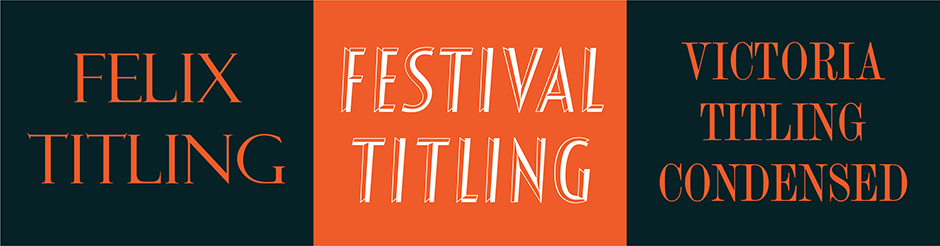
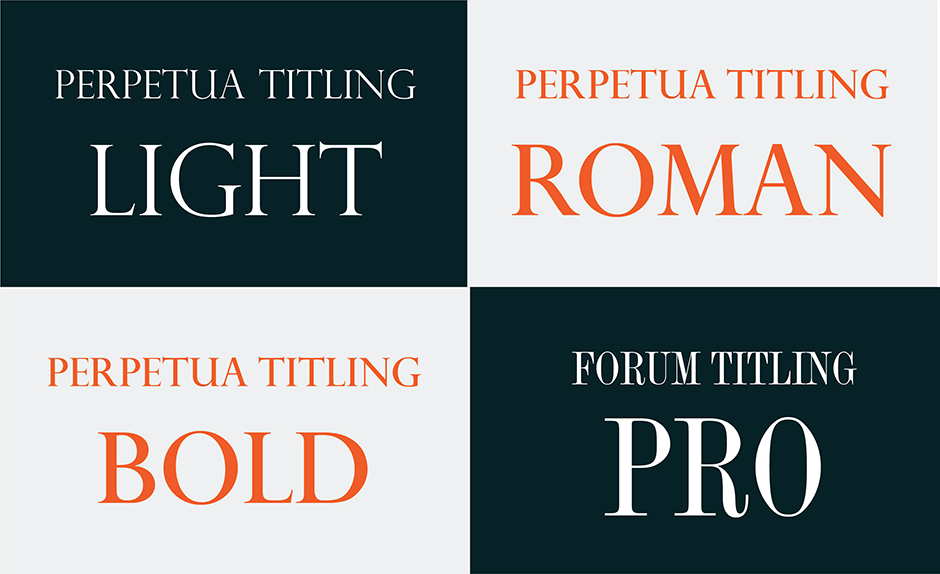
Eine der traditionellsten Fonts derzeit , die Designer zur Verfügung steht, ist Trajan™ von Carol Twombly. Basierend auf den monumentalen Buchstaben der antiken Trajanssäule ist diese zweigewichtige Familie eine Hommage an das, was viele als Inbegriff des römischen Alphabets betrachten. Mit Ausnahme des ausladenden Schwanzes des "Q" ist dies ein Design ohne Verzierungen oder Schnörkel.
Die Titelseite Fonts hat einen hohen Stellenwert und ein anspruchsvolles Auftreten. Sie sind elegant, raffiniert und - manchmal - dramatisch. Ihr natürliches Umfeld sind Buchtitel, Urkunden, Filmtitel, Zeitschriftencover und Beschilderungen, aber sie können auch in Überschriften, Untertiteln und als Anfangsbuchstaben eine starke Kommunikationswirkung haben. Sie brauchen vielleicht nicht viele Titel Fonts, aber ein paar davon werden sich als wertvolle typografische Investition erweisen.